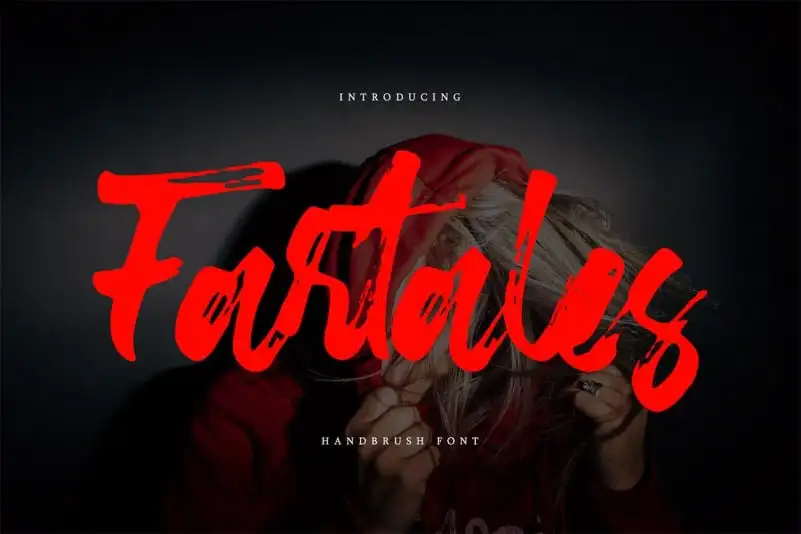
Fartales Brush Font – Download Grátis
A Fartales Brush Font é uma tipografia casual desenhada à mão, produzida pela Vztype com uso de um canivete deslizante seco. Esta elegante fonte é ideal para qualquer projeto que você esteja planejando, desde a criação de logomarcas e identidades corporativas até redes sociais e DIY criativos. Com seu traçado delicado, essa fonte permite ao designer explorar uma variedade de estilos únicos e pessoais, tornando-a perfeita para personalizar qualquer projeto. Uma ótima escolha para aqueles que buscam um toque casual e artesanal em seus materiais digitais. E o melhor, tudo isso vem da confortável e prática tecnologia dos 99designs, a plataforma onde essa fonte foi criada.